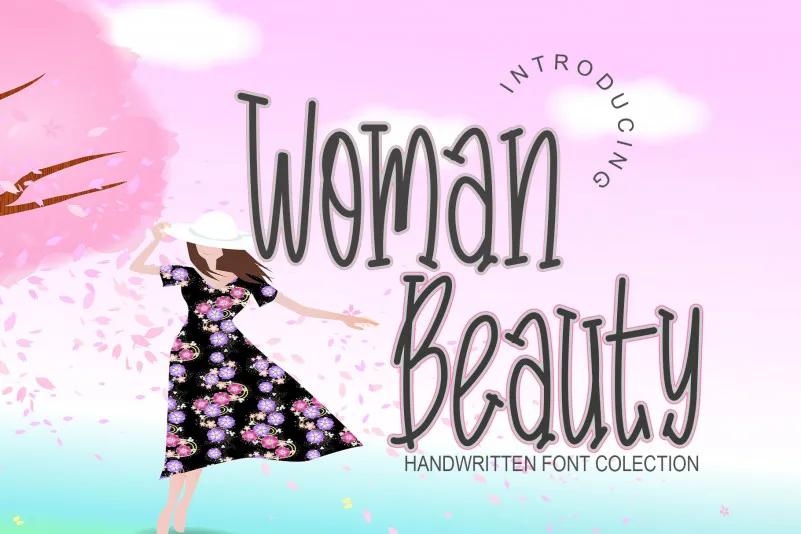
Woman Beauty Font
Esta fonte Woman Beauty é uma elegante e delicada escrita manuscrita. Suas letras distintas e redondas são verdadeiros trabalhos de arte que destacam-se por sua perfeição. Ideal para ambientes gráficos sofisticados, a fonte Woman Beauty traz um toque refinado às suas criações. Não importa o design, seja uma assinatura ou uma marca, ela dará um brilho especial à sua identidade visual. Designer da fonte é kateengciu e foi classificada como Display Fonts. Seja você designer de rótulos, revistas ou mesmo aplicativos móveis, a Woman Beauty será o grampo perfeito para seus projetos que exigem elegância natural.